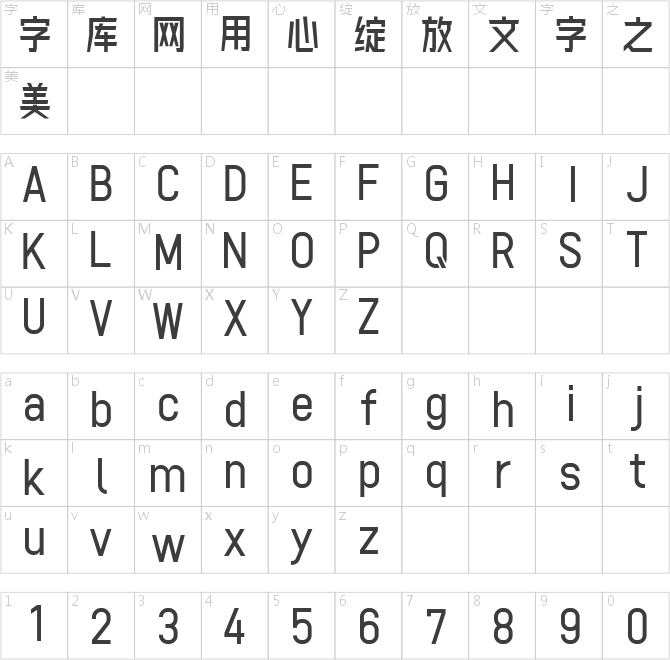
字體名稱: 金山云技術體
“金山云技術體”是一款無襯線體,提供一種標準版字重,文字參照GB2312簡體中文編碼字符標準。包含國標一級、二級字庫漢字6763個,外文及數字符號804個,總字符數7567個。
金山云技術體字體字庫是一款讓人賞心悅目、百看不厭的中文字體,適合各類廣告和產品包裝設計應用,字體大小3.17MB,格式為ttf字體,上傳用戶是青檸檬,作者/版權方為金山云